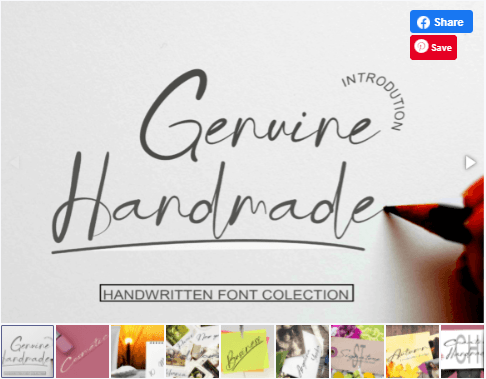
Genuine Handmade Font
Genuine Handmade - это элегантный шрифт с современной атмосферой и безупречной формой, вдохновленный вневременной классической каллиграфией. Не слишком тонкий и не слишком толстый, сбалансированный и разнообразный, этот шрифт был разработан, чтобы подчеркнуть красоту ваших проектов.